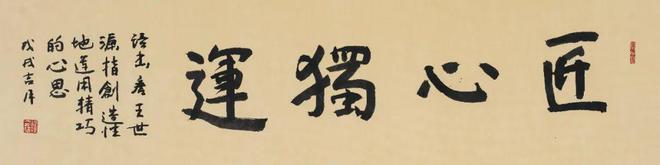
《说文写字:汉字释义与字体书法》新书首发式在北京举行
1月8日,由启全广州文化有限公司、创意园承办的《说文写字:汉字释义与字体书法》新书首发式在北京首创郎园“良阅城市书房”举行。现场活动由著名导演卫青主持。中国人民大学美术学院副院长刘明才,华辰拍买董事长甘学军,该书总策划、著名画家黄庆辉分别致辞,对新书的出版给予了充分的肯定,纷纷表示该书具有较高的文献和艺术价值。
程伟,1957年11月出生,上海书法家协会会员,曾任宁夏书法家协会副主席,是一位从根上追逐书法学问的学界长者。程伟认为,“芥子容乾坤、字中有历史”,书法看起来是写字,但其实是在写历史、写文明、也是在写中华优秀文化。其书古拙质朴、平实坚定,无流美炫技之弊,笔墨造型间一股坚实淡定的精神超然内在,作品多次入选地方和部队书法展。
《说文写字:汉字释义与字体书法》由岭南美术出版社出版发行,系程伟潜心数年研究创作的成果。程伟融汉字学和书法学为一体,以“说文”与“写字”相结合,将每个汉字的本意和衍生意义,以及篆、隶、楷、行、草书……的各种写法予以呈现,使读者同时满足知识的收获与艺术的熏陶。
收录该书中的每一个汉字,皆依据《说文解字》《康熙字典》《新华字典》等权威工具,寻根问底查证其释义的古今流变;在写法上,则查阅大量书法字典和名家碑帖,深研古法,严循规范,一笔一画都方圆达标,极致演绎中国文字的审美趋向与轨迹。毫无疑问,该书具有某种奠基性意义,它担当起了入门级、必备级、工具级的责任,是每一个想了解中国汉字和书法艺术者理想的案头卷。
程伟书法
据悉,程伟已经积累近万幅书稿和练习作品,计划用3年时间完成常用3000个汉字的释义与书法融合,集结出版10部《说文写字》系列著作,倾心打造一套跨艺术门类、多学科交叉融合的教科类典籍。
程伟书法